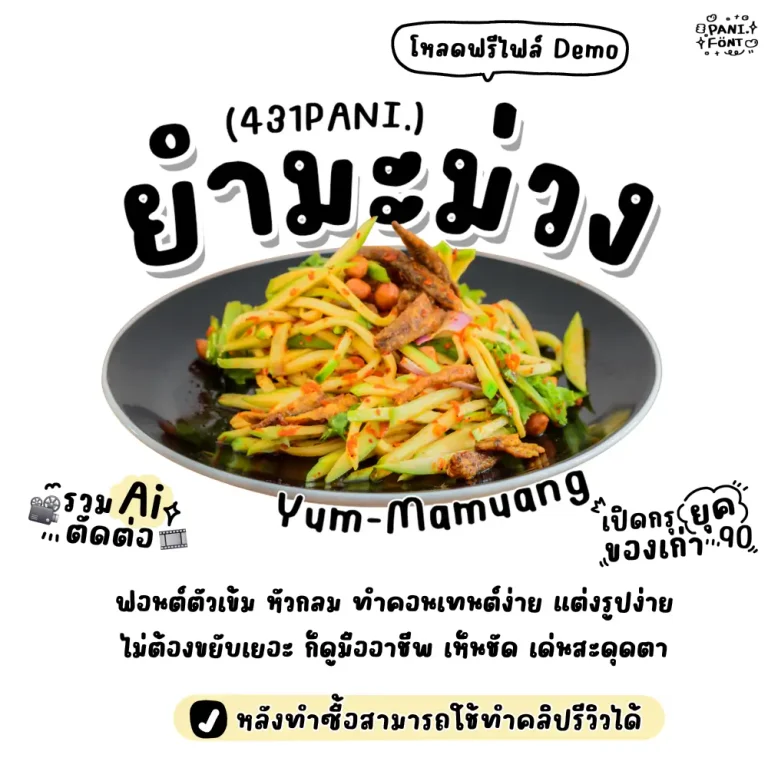
ฟอนต์ตัวหนาๆ ชัดๆ ใช้ทำหัวข้อก็เห็นชัด อ่านง่าย จะใช้เป็นรายละเอียดต่างๆ ก็สบายตา ใช้งานได้หลายรูปแบบ ทั้งหัวข้อคอนเทนต์ก็เด่น จะแต่งป้ายสินค้าก็ดูดี จะจด Goodnote/Canva ชุดนี้เอาอยู่